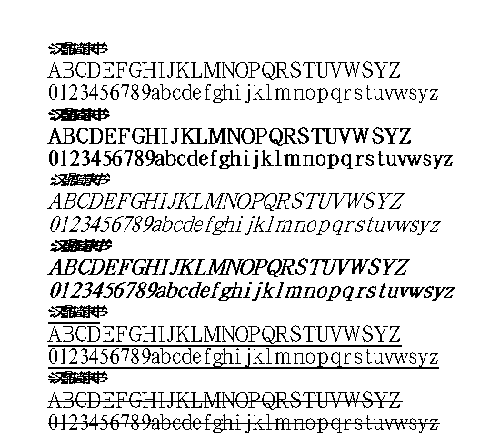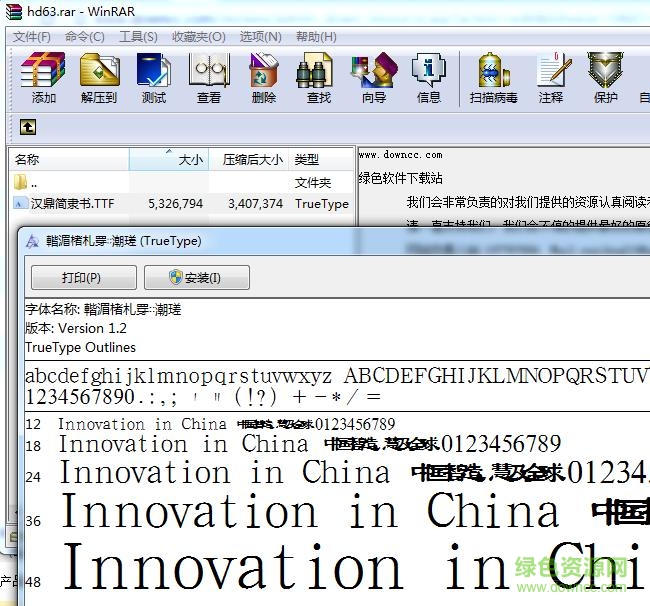
漢鼎簡隸書是獨(dú)特的隸書體字體樣式文件,擁有古風(fēng)隸書的眾多優(yōu)點(diǎn),在諸多方面廣為流傳使用,曾經(jīng)是眾多學(xué)子文豪喜愛的字體,如今廣泛應(yīng)用到古風(fēng)藝術(shù)品的字體題詞上以及現(xiàn)代工藝品字體創(chuàng)作等!
隸書是漢字中比較常見的一款字體,它具有莊重的視覺效果,隸書的書寫效果略微寬扁,橫畫長而直畫短。用戶可以將其用于海報(bào)、廣告、婚禮等設(shè)計(jì)方面,如果需要簡體隸書,可以下載本款字體。